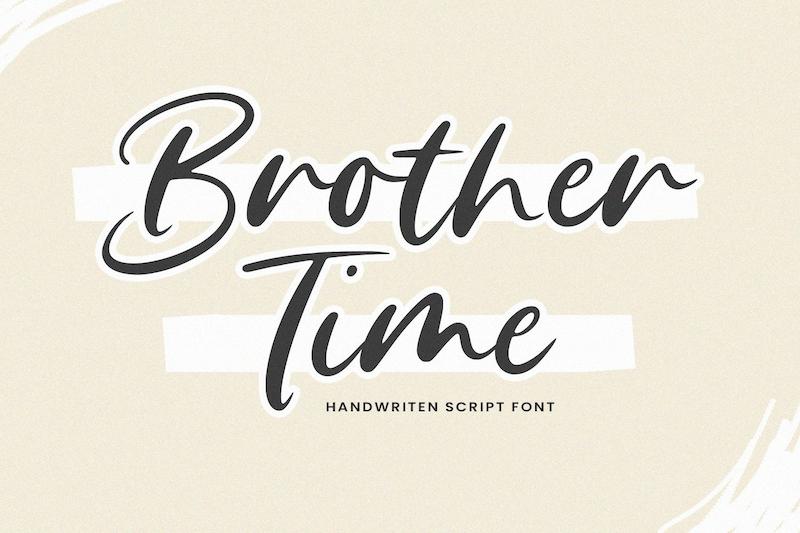
فونت انگلیسی دست‌نویس خوش‌فرم الگانت (Brother Time)
معرفی فونت برادر تایم
برادر تایم یک فونت دست‌نویس است که با دقت فراوان و به‌طور ویژه برای شما خلق شده است.
برادر تایم برای بسته‌بندی محصولات، پروژه‌های برندینگ، مجلات، شبکه‌های اجتماعی، عروسی یا صرفاً برای بیان کلمات روی پس‌زمینه، مناسب است.
این فونت شامل موارد زیر است:
• حروف بزرگ و کوچک
• اعداد و علائم نگارشی
• پشتیبانی چندزبانه
• طبقه‌بندی: اسکریپت و دست‌نویس